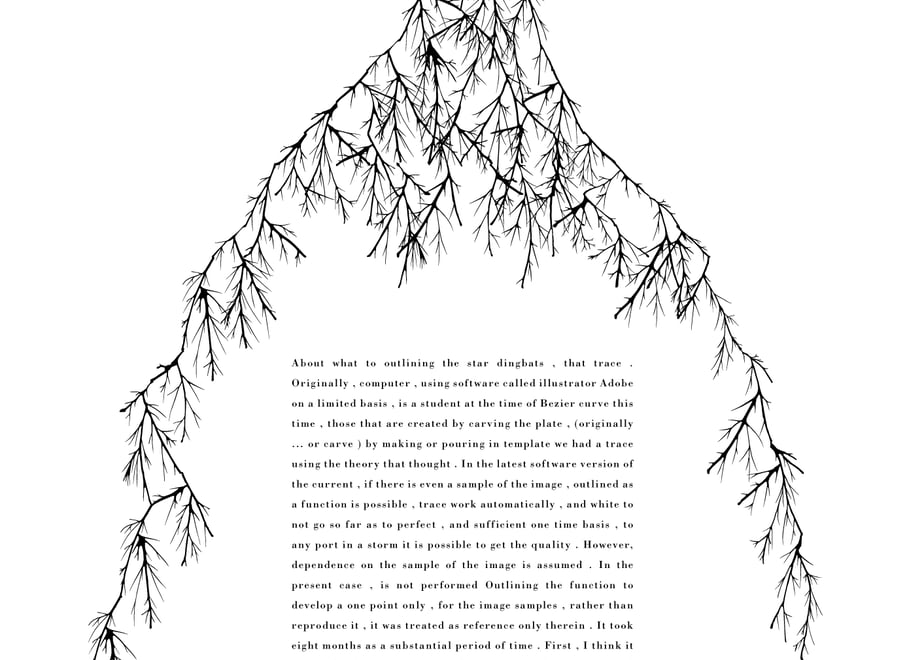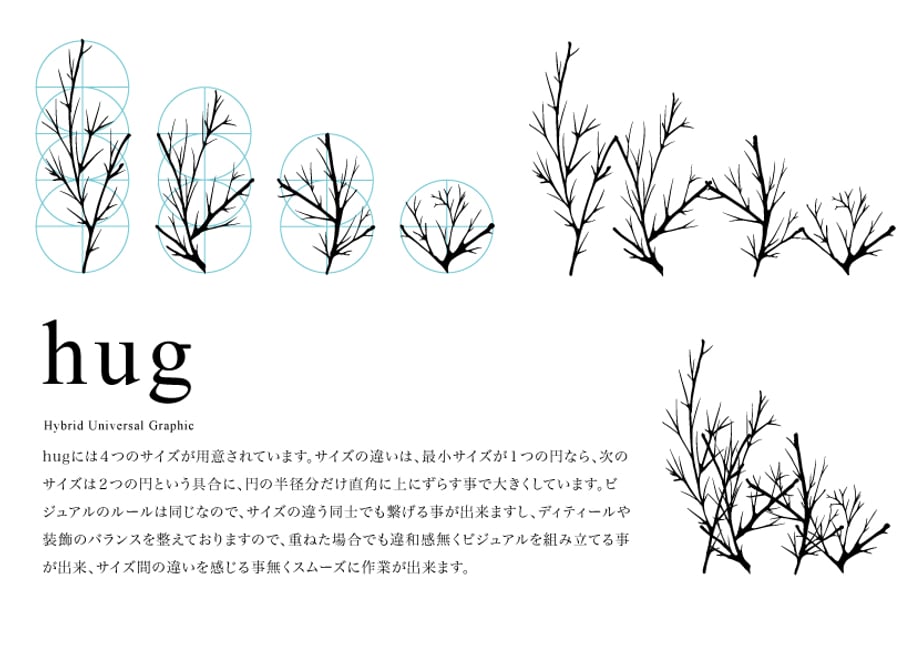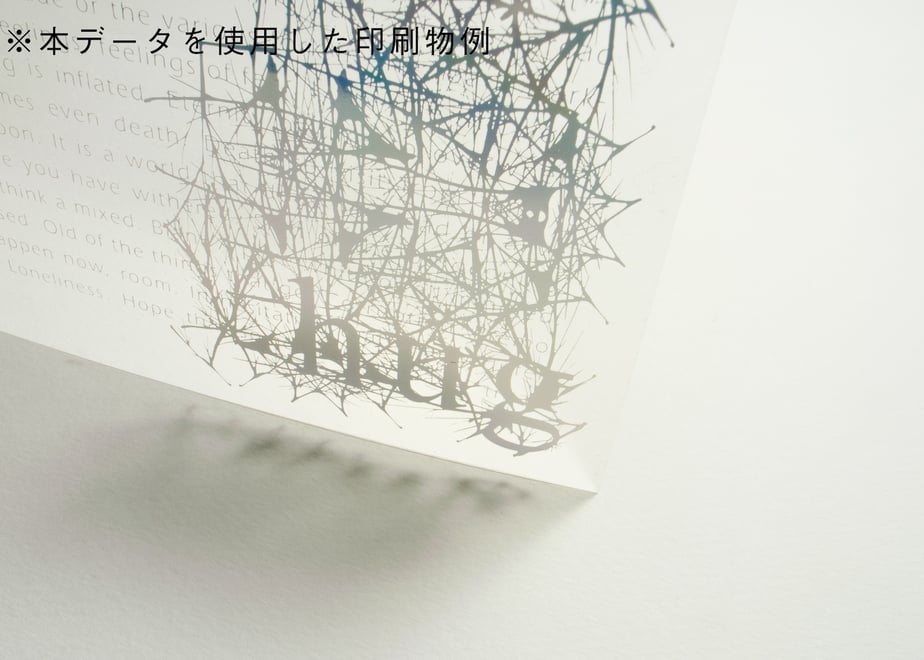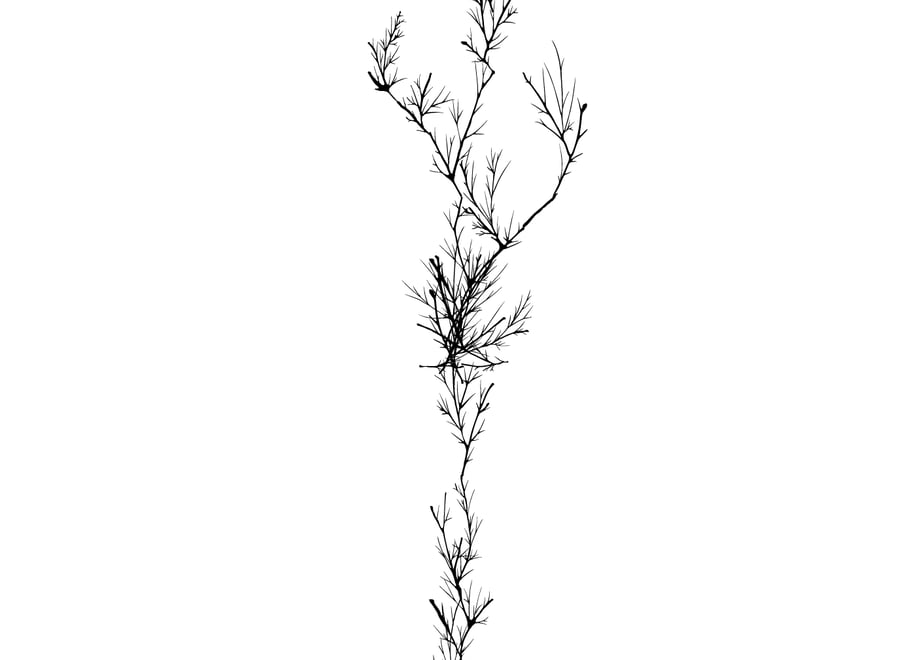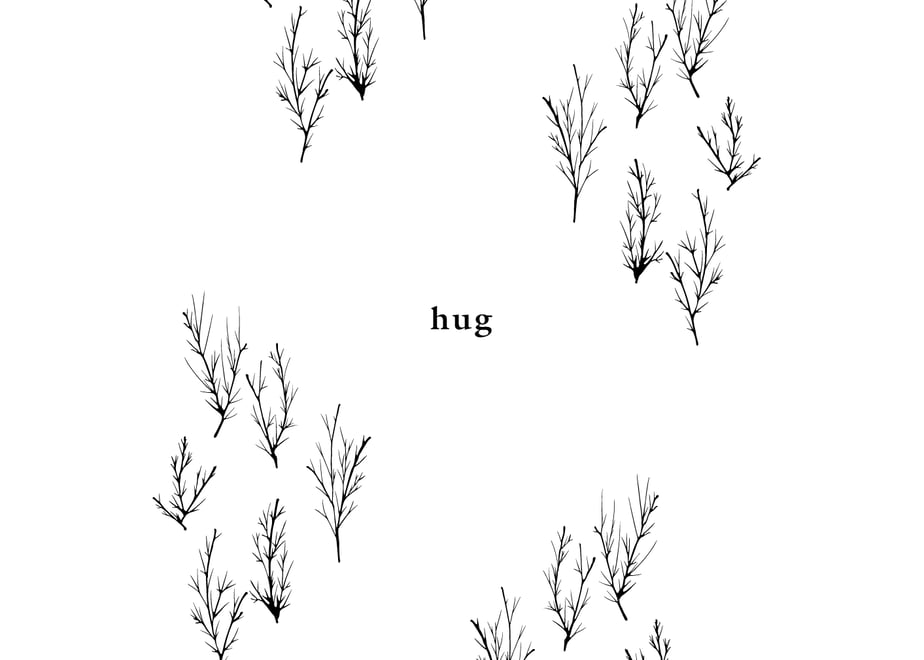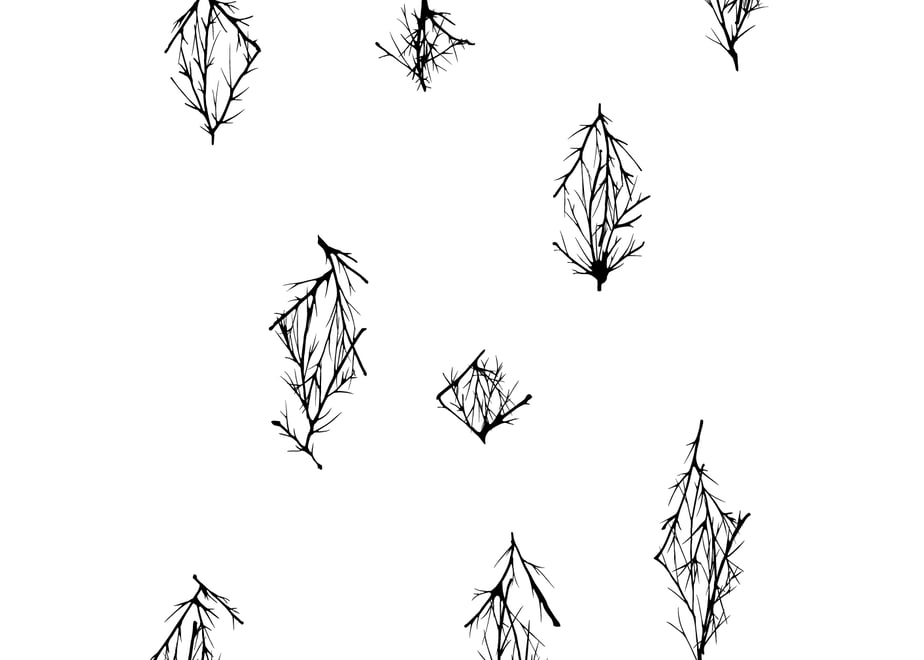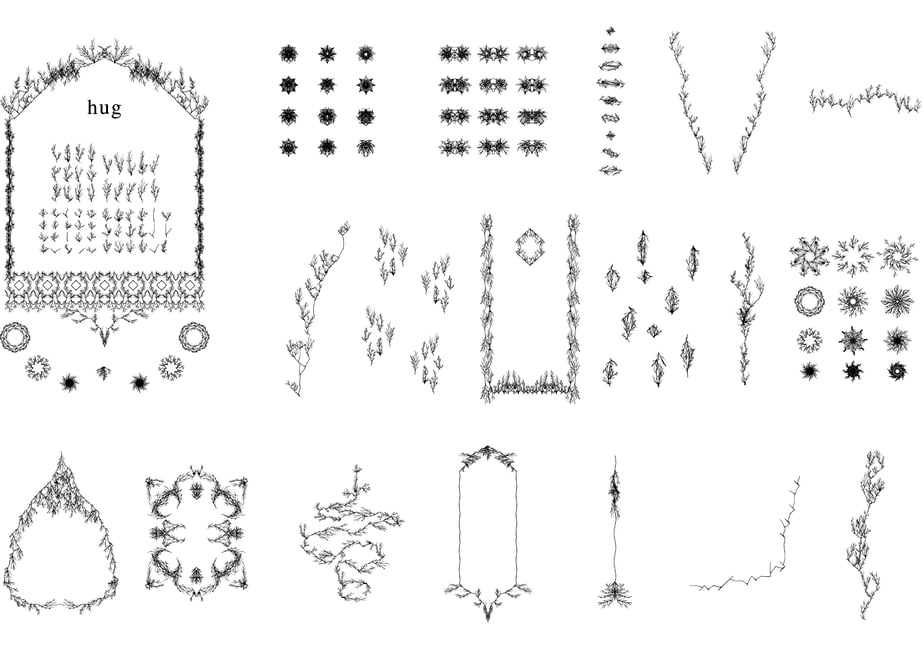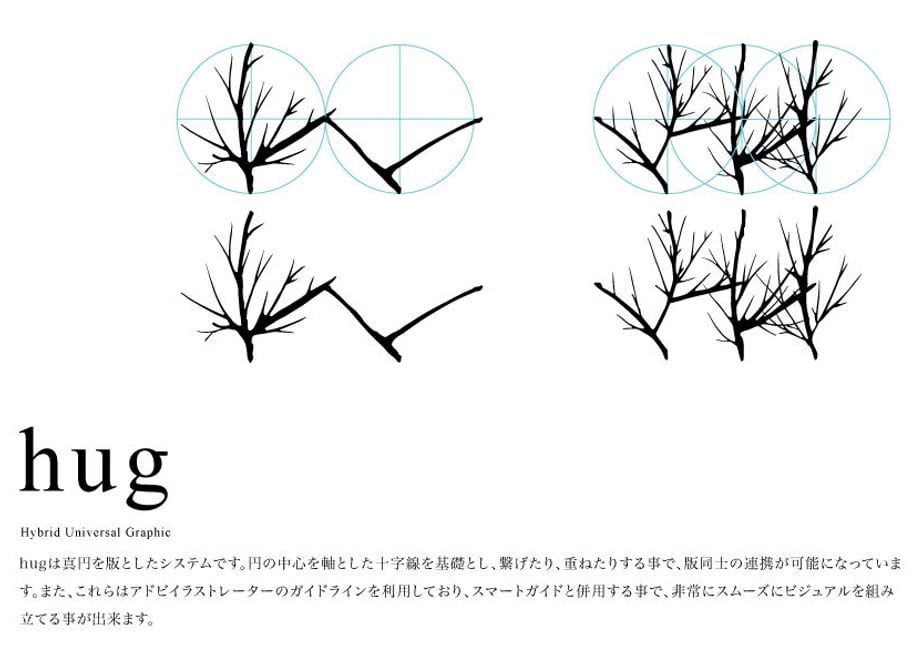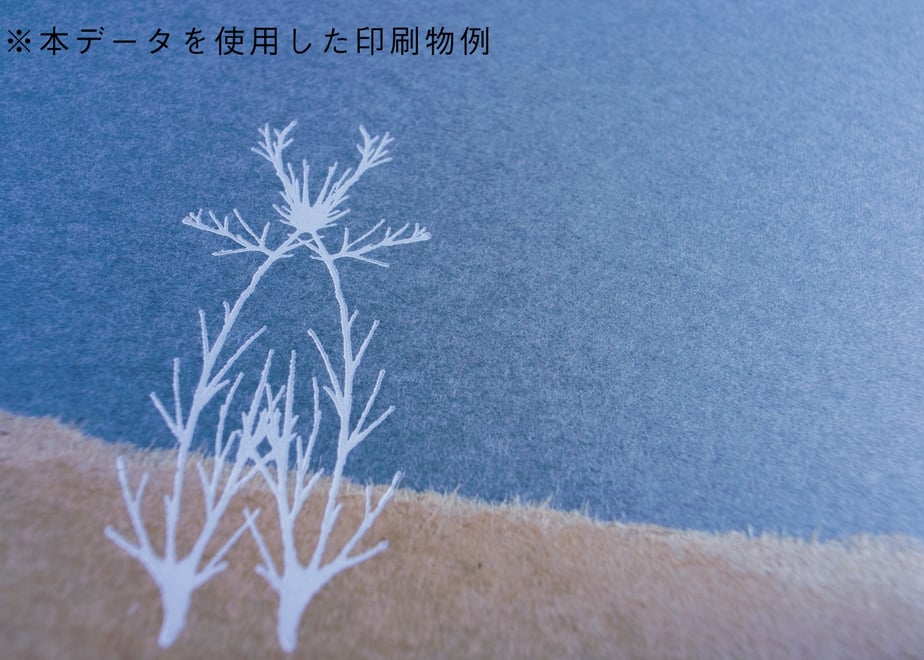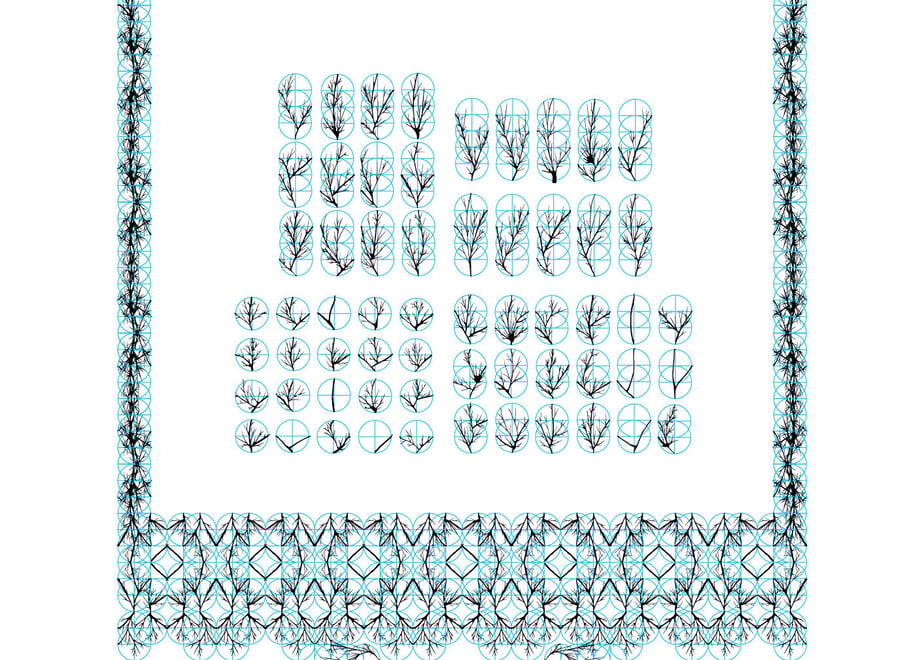
装飾活字:hug
Decorative type with a dead tree motif.
A set of 60 types of objects with different shapes, all of which are converted into outlines, and 18 types of composition samples using these objects. The file will be a full set of Adobe Illustrator format (.ai).
枯れ木をモチーフにした装飾活字。
全てがアウトライン化された形の違う60種類のオブジェクトと、そのオブジェクトを利用した18種類の組み見本のセット。ファイルはアドビイラストレーターの形式(.ai)のフルセットになります。